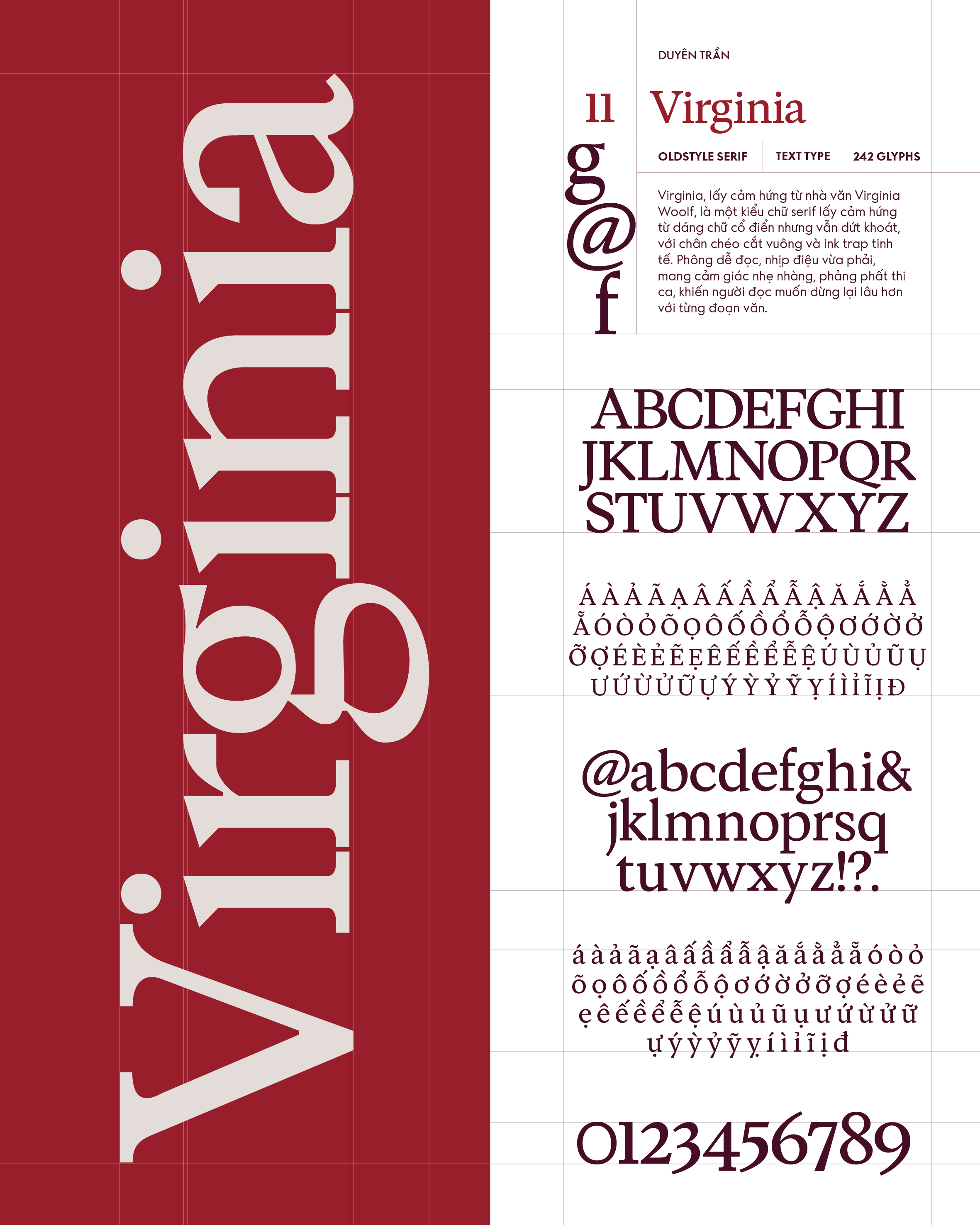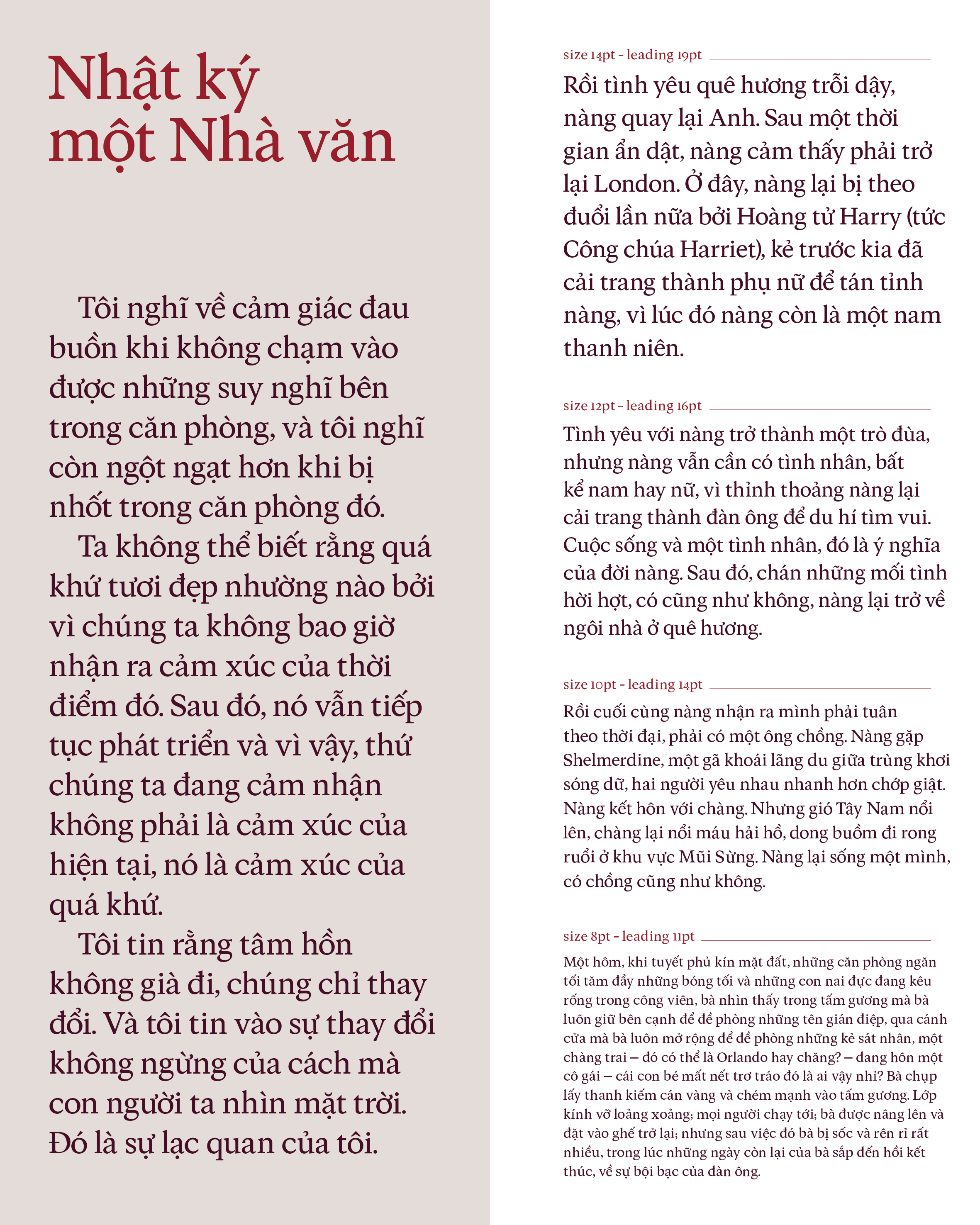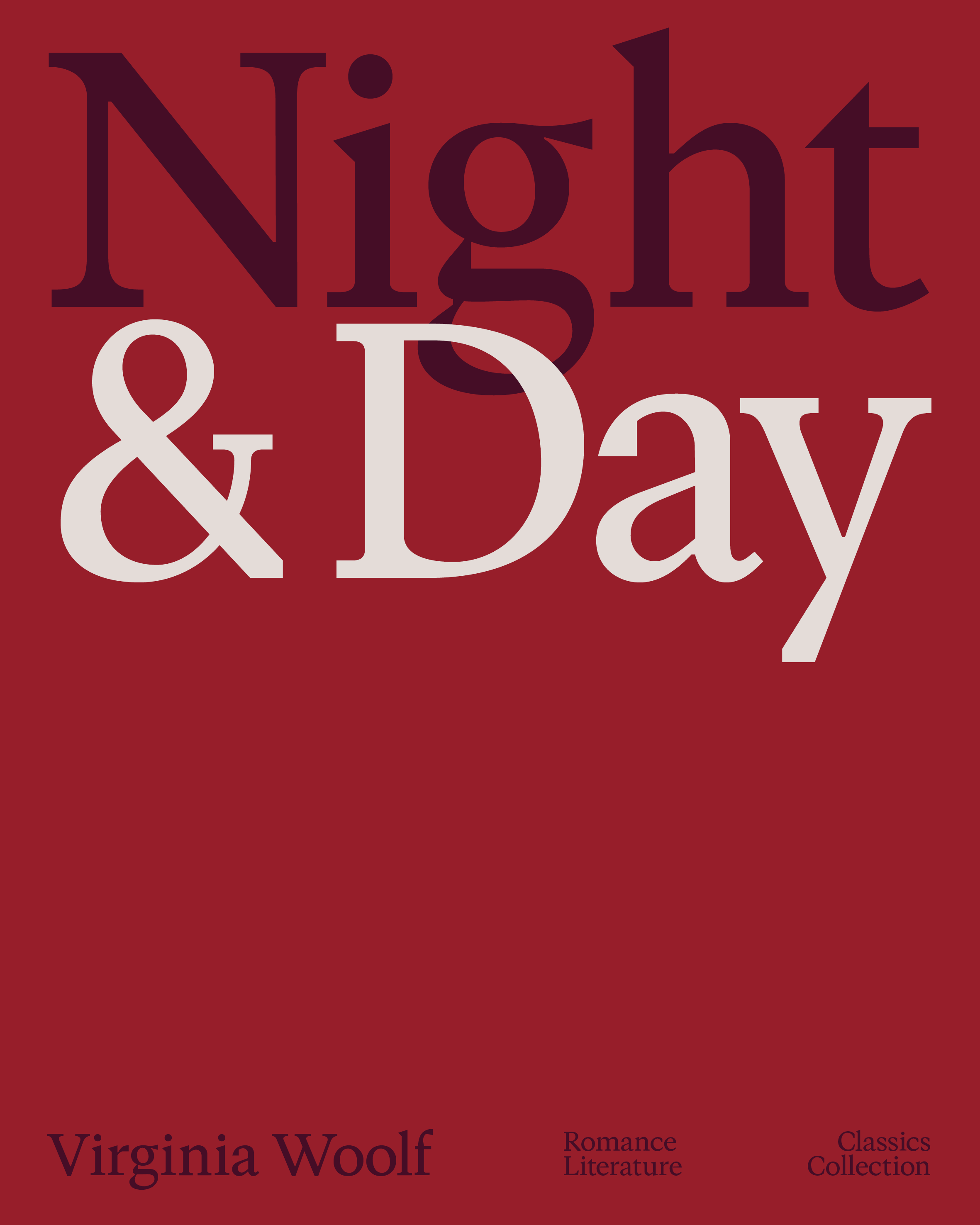
Virginia
Về Virginia: Virginia, lấy cảm hứng từ nhà văn Virginia Woolf, là một kiểu chữ serif lấy cảm hứng từ dáng chữ cổ điển nhưng vẫn dứt khoát, với chân chéo cắt vuông và ink trap tinh tế. Phông dễ đọc, nhịp điệu vừa phải, mang cảm giác nhẹ nhàng, phảng phất thi ca, khiến người đọc muốn dừng lại lâu hơn với từng đoạn văn.
Humanist Serif
Text
Duyên Trần